在这篇博文中,我们将探索 2023 年 20 种最佳方形字体(免费和付费),它们可以增强您的设计并吸引受众。
现在,您可能想知道,为什么使用方形字体? 那么,方形字体提供了大胆而现代的外观,可以使您的文本脱颖而出并吸引注意力。
它们用途广泛,可用于各种设计项目,从徽标和海报到网站标题和社交媒体图形。 方形字体凭借简洁的线条和几何形状,为任何设计增添了一丝精致和专业精神。
但这是最好的部分 - 我们已经为您完成了研究! 在本文中,我们列出了 2023 年 20 种最佳方形字体。无论您是在寻找免费选项还是愿意投资高级字体,我们都能满足您的需求。
我们将为您提供有关每种字体的一些有趣的统计数据和事实,帮助您做出明智的决定,确定哪种字体适合您的需求。
因此,喝杯咖啡,准备好为您的下一个设计项目发现完美的方形字体。 请继续关注我们深入细节并探索方形字体的不可思议的世界!
最佳高级方形字体
希望为您的设计项目增添一丝现代优雅的气息? 我们精选的优质方形字体就是您的最佳选择。
准备好使用这些令人惊叹的字体将您的设计提升到一个新的水平,这些字体一定会吸引您的观众。 不要错过查看我们在下面为您准备的一系列精美的方形字体!
格特拉克
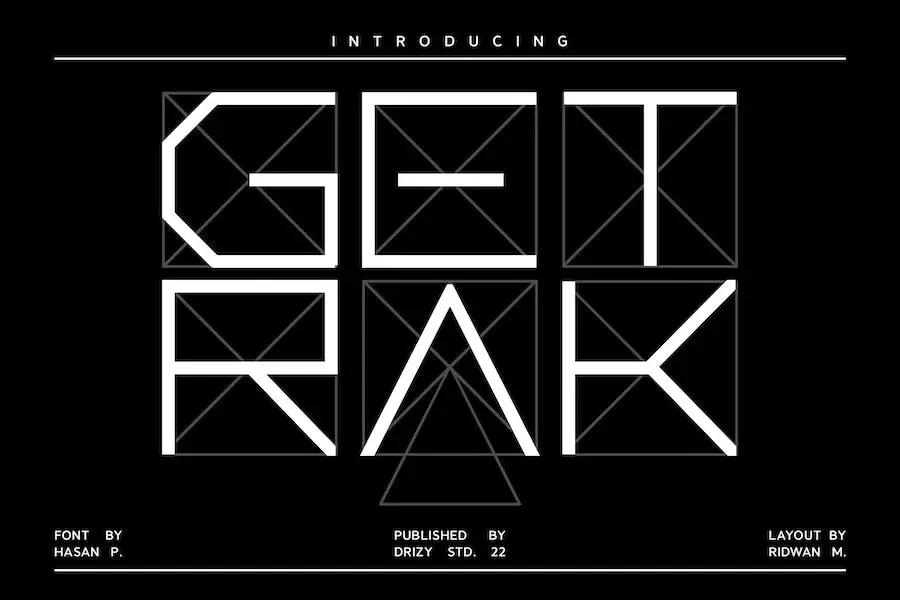
Getrak 是 Drizy studio 的一款几何方形字体,非常适合为您的设计项目添加现代感。 它提供了您需要的所有基本样式,并且可供购买和下载。
凭借其全部大写、数字和标点符号,您拥有创建令人惊叹的专业设计所需的一切。 Getrak 还支持多种语言,使其用途广泛,适合各种项目。
泡芙广场
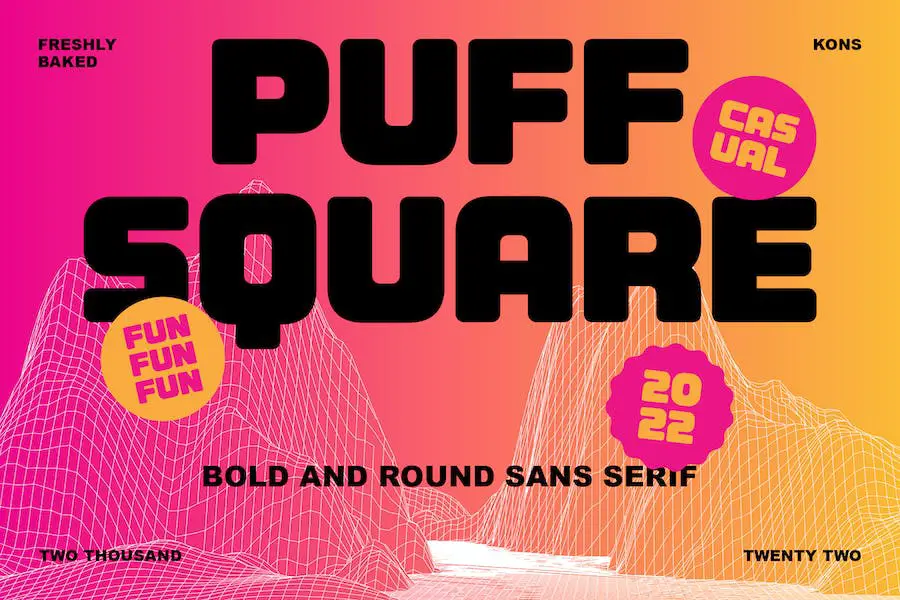
Puff Square 是一种厚实、大胆且有趣的无衬线显示字体,为您的视觉美感增添了俏皮和休闲的氛围。 这种现代方形字体具有圆角,非常适合希望改进项目设计的图形设计师。
无论您是在设计徽标、海报还是网站,Puff Square 的几何和块状风格都会让您的设计脱颖而出。 它与 Google 和 Adobe 兼容,使其可以轻松地在 Word 和 Canva 等各种设计程序中使用。
您甚至可以使用 Puff Square 进行纹身设计,以增添额外的创意。 在您的下一个设计项目中拥抱 Puff Square 的多功能性和独特魅力!
夏日广场
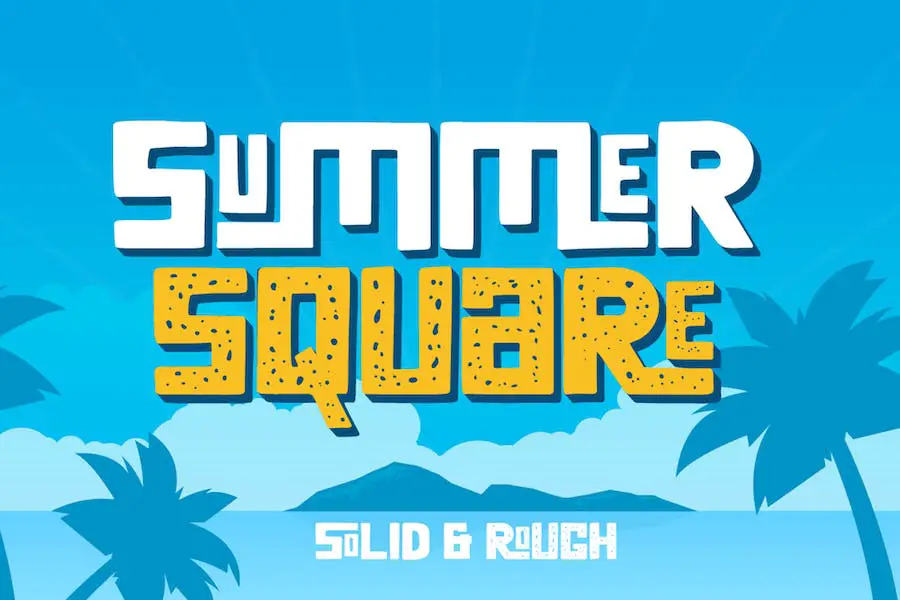
'Summer Square 是一款复古的全大写字体,提供干净和粗犷的风格。 作为市场上顶级的现代方形字体之一,它为您的设计项目带来一丝怀旧之情。
凭借其块状和几何设计,这种字体非常适合创造大胆而引人注目的美感。 无论您是在设计徽标、海报,甚至是纹身设计,Summer Square 的功能都足以满足您的需求。
与 Adobe 和 Canva 等流行的设计工具兼容,可以轻松地将这种字体合并到您的项目中。 不要错过通过 Summer Square' 为您的设计添加独特和魅力的元素。
讣告
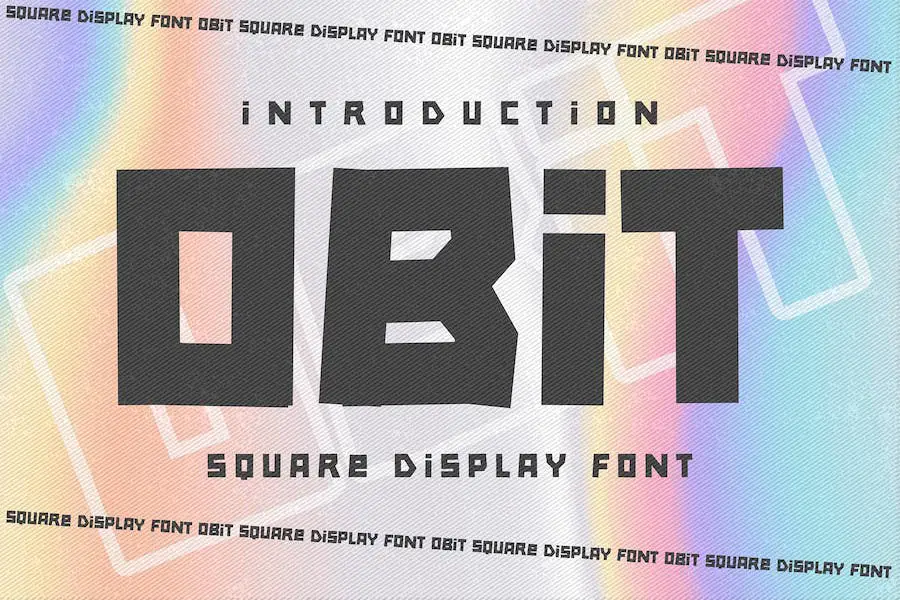
OBIT 是一种方形显示字体,可为您的项目带来自然纹理和优雅的风格。 它非常适合为您的摄影作品添加水印、创建徽标和品牌、设计邀请函、广告、产品包装等等。
这种手工制作的字体具有自然的手写感觉,为您设计的每个细节增添了美丽的触感。
您可以在 PC 和 Mac 上使用 OBIT,让广大设计师都能使用它。 它包括标准字形,并与 Adobe Illustrator、Photoshop 和 InDesign 等流行设计软件兼容。
方形
'Squarix 是一种无衬线显示字体,非常适合各种设计项目。 从徽标品牌到编辑设计,从文具设计到运动设计,这款字体都能满足您的需求。
它的多功能性延伸到 80 年代复古设计、游戏行业、音乐海报、博客设计、现代广告、卡片邀请函、艺术名言、电影、家居装饰、书籍封面、特别活动等等。
MBF神经质
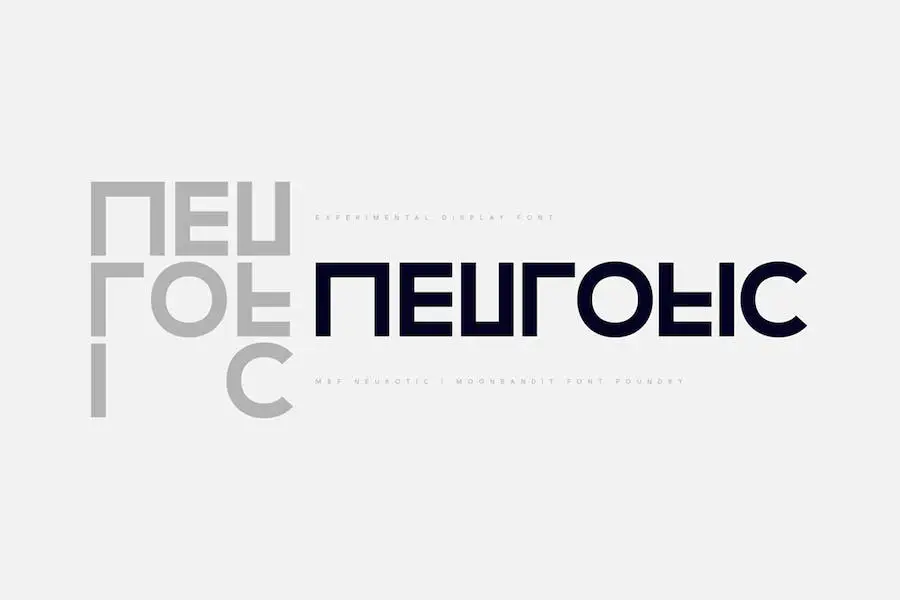
MBF Neurotic 是一款现代简约的方形无衬线字体,可为任何设计项目增添独特的触感。 凭借其对角度和直线的实验性组合,这种字体在人群中脱颖而出。
您可以使用大写和小写字母轻松访问不同的样式。 它非常适合海报、徽标、标题、T 恤设计等。
正方形
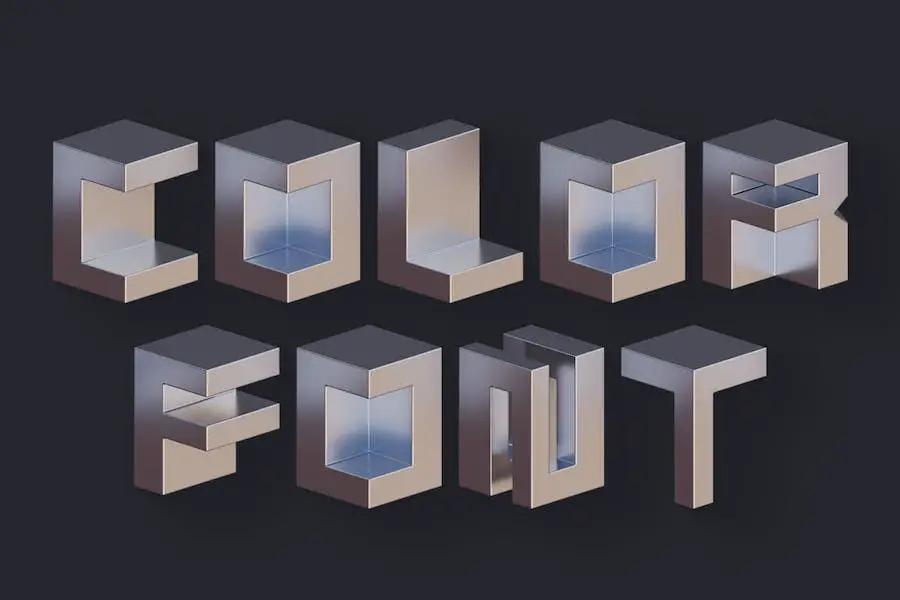
Squares 是一种颜色或 SVG OpenType 字体,仅适用于 Photoshop CC 2017+、Illustrator CC 2018 和某些 Mac 应用程序。 它具有方形、未来感、金属感和几何 3D 风格。
这种字体非常适合为您的图形设计项目添加独特的风格。 为了确保字体正确显示,请确保创建一个包含整个窗口的文字区域。
如果您发现任何字母延伸到该区域之外,只需调整间距即可正确查看它们。 此外,如果您使用 Adobe Photoshop 并注意到彩色字体上有清晰的边框,请务必将字体设置为平滑样式。
梅斯特罗显示器
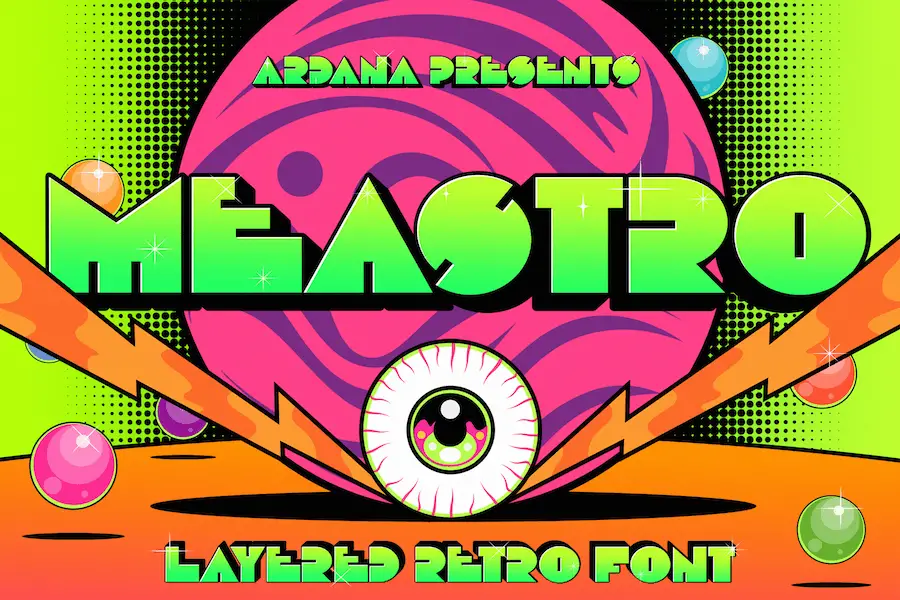
Meastro Display 是一种字体,提供独特的块状和方形设计,为您的设计增添经典和复古的气息。
凭借其复古字体,它是标识、T 恤、复古徽章、复古报价、品牌、包装、海报、招牌甚至社交媒体内容的理想选择。
这种字体完美融合了怀旧与现代设计美学,使其成为任何项目的多功能且引人注目的选择。
方形爆炸
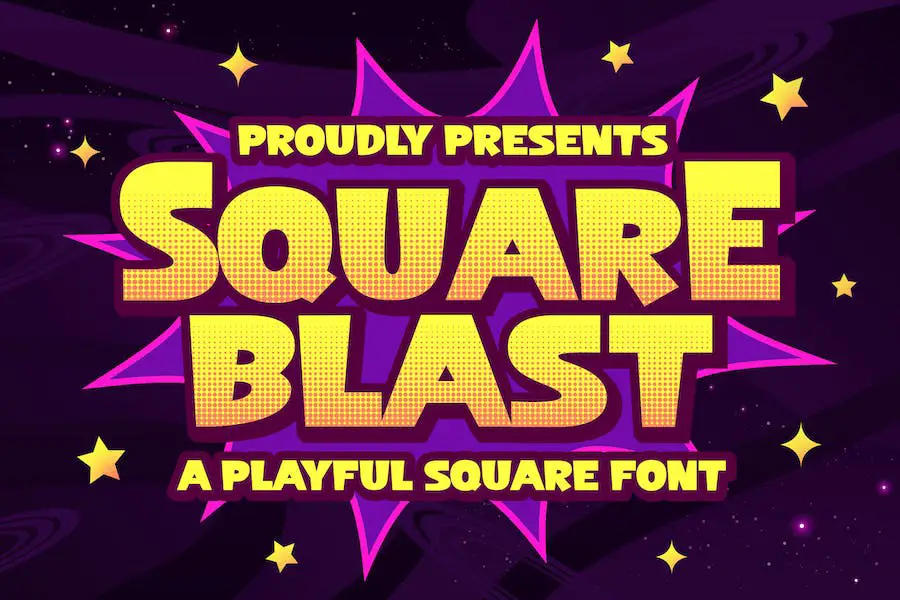
Square Blast 是一款有趣的方形字体,其灵感来自于有弹性的卡通风格的排版。 这种字体以对美学的敏锐眼光而设计,非常适合需要一丝奇思妙想和俏皮感的设计。
无论是书籍封面、儿童读物、漫画、海报、包装、商品还是引人注目的标识,Square Blast 一定会让您的项目更具吸引力和吸引力。
沼泽地
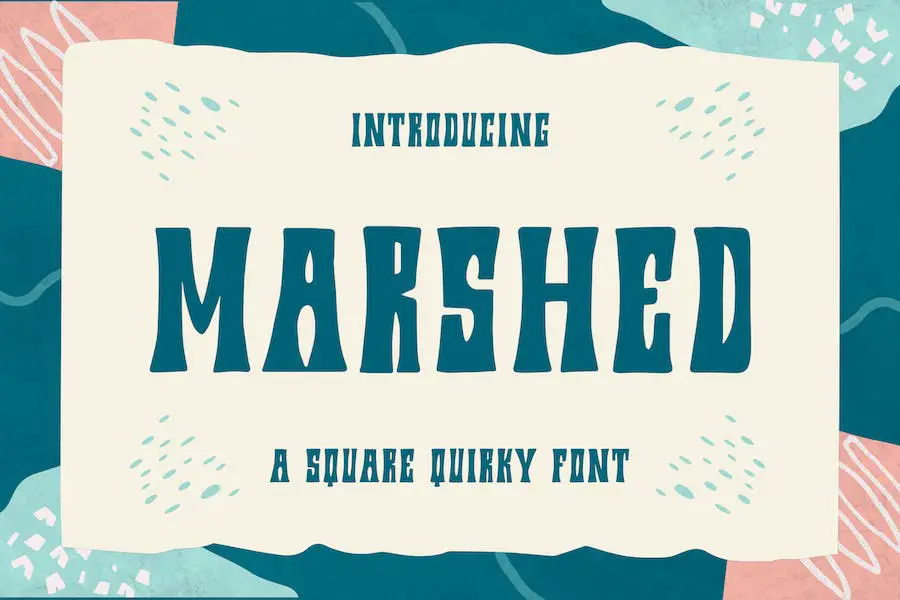
Marshed 是一种有趣且古怪的显示字体,可为任何设计项目带来独特的触感。 凭借其 PUA 编码,访问所有装饰字形和花饰变得轻而易举。
这种字体特别适合儿童主题的设计,但它的多功能性还不止于此。 无论您是在制作徽标、邀请函还是任何创意项目,Marshed 都有潜力提升您的创作水平。
该字体具有大写和小写字母,可让您灵活地混合搭配以获得个性化外观。 它还带有一系列符号和标点符号,让您可以为您的设计增添额外的魅力。
方队
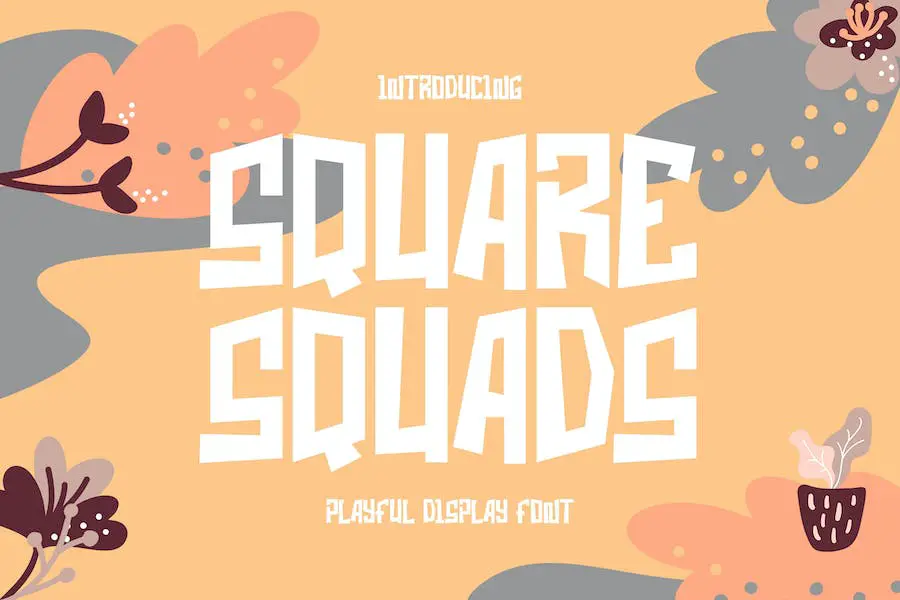
Square Squads 是一种有趣的显示字体,可为任何项目增添一丝乐趣和酷感。
无论您是在设计时装设计、专辑封面、徽标、品牌、杂志布局还是社交媒体内容,这种字体都是完美的选择。 它甚至也适用于其他类型的项目!
《Square Squads》的亮点之一是其奇特而有趣的设计。 凭借其独特的字符集,您可以创建引人注目的设计,在人群中脱颖而出。
格劳格斯
Graugs 是一种方形无显示字体,具有粗体笔划和有趣的字符。 它还包括连字和替代,为您的工作增添创意。 该字体用途广泛,支持 100 多种不同语言,适合各种设计项目。
无论您需要用于徽标设计、社交媒体、电影标题、书名,甚至是长文本字母的字体,Graugs 都可以帮助您创建令人惊叹的视觉效果。
它还与脚本或衬线字体完美搭配,使其成为辅助文本的绝佳选择。 借助 Graugs,您可以让您的设计真正脱颖而出。
街区广场
Block Square 是一种精美的手写字体,具有书法风格,非常适合为您的项目增添一丝优雅。
无论您是在制作邀请函、贺卡、品牌材料、名片、报价单还是海报,这种字体都一定会脱颖而出。
Block Square 的突出特点之一是它的多语言支持。 这意味着您可以轻松地将不同的语言融入您的设计中,没有任何麻烦。
石海
Stone Ocean 是一种有弹性的方形字体,非常适合为您的设计项目增添俏皮感,特别是当您正在设计热带或儿童主题的作品时。
凭借其有趣和充满活力的风格,这种字体将为您正在从事的任何项目带来欢乐和兴奋的感觉。
石海的突出特点之一是其独特的方形形状。 这些字母具有大胆而坚实的外观,使它们在页面上具有很强的存在感。 这使得字体具有高度可读性和影响力,确保您的信息有效传达。
方形霓虹灯
Square Neon 是一种彩色或 SVG OpenType 字体,最适合与 Photoshop CC 2017+、Illustrator CC 2018 等设计软件和部分 Mac 应用程序配合使用。 这是一项新技术,可让您为版式添加充满活力、引人注目的颜色。
需要注意的一件重要事情是,如果您想在 SVG 字体上实现逼真的笔刷效果,则应该在浅色背景上使用深色字体并使用 Multiply 图层效果,或者在深色背景上使用浅色字体并使用 Screen 图层效果。
这将有助于为您的设计提供额外的深度和真实性。 将字体设置为平滑的样式至关重要,尤其是当您在 Adobe Photoshop 中发现彩色字体上有任何脆边时。
最佳免费方形字体
希望为您的设计增添现代感和几何优雅感? 我们收集的最好的免费方形字体就是您的最佳选择。 看看这些令人惊叹的选项,将您的项目提升到一个全新的水平。
平方2
Squared2 是 Patrik Losengo 创建的免费字体,非常适合希望增强项目设计的图形设计师。 这种方形字体为任何设计增添了现代和时尚的触感,使其在人群中脱颖而出。
Squared2 具有简洁的线条和几何形状,用途广泛,可用于徽标、标题和正文。 其大胆的外观为任何设计增添了一丝精致和专业精神。
此外,由于 100% 免费,对于预算紧张的设计师来说,这是一个经济实惠的选择。 因此,尝试一下 Squared2,用这种时尚且多功能的字体将您的设计提升到一个新的水平。
弗利巴什
Pixel Sagas 的 Flipbash 是一种可以显着增强图形项目设计的字体。 这种方形字体提供独特而现代的外观,非常适合为您的设计带来新鲜和时尚的吸引力。
Flipbash 凭借其笔直的边缘和简洁的线条,为任何设计增添了时尚和专业的触感。 无论您是要创建徽标、海报还是网站,这种字体都会使您的文本脱颖而出并吸引观众的注意力。
复仇者
Avenger 是 Iconian Fonts 提供的一种字体,完全免费供个人使用。 这种方形字体非常适合希望通过简洁而现代的设计来增强其项目的图形设计师。
凭借其独特的形状和清晰的线条,Avenger 为任何项目增添了时尚和专业的感觉。
无论您是在制作徽标、海报还是网站,这种字体一定会让您的设计脱颖而出。 其独特的风格易于阅读,同时仍能吸引注意力。 使用 Avenger 为您的项目提供所需的优势。
四合院
Typodermic Fonts 的 Quadrangle 是一款锋利、机器人般的标题尖叫器,它将为您的设计项目带来技术优势。 这种字体具有方形和清晰的线条,非常适合为您的信息添加现代和未来感。